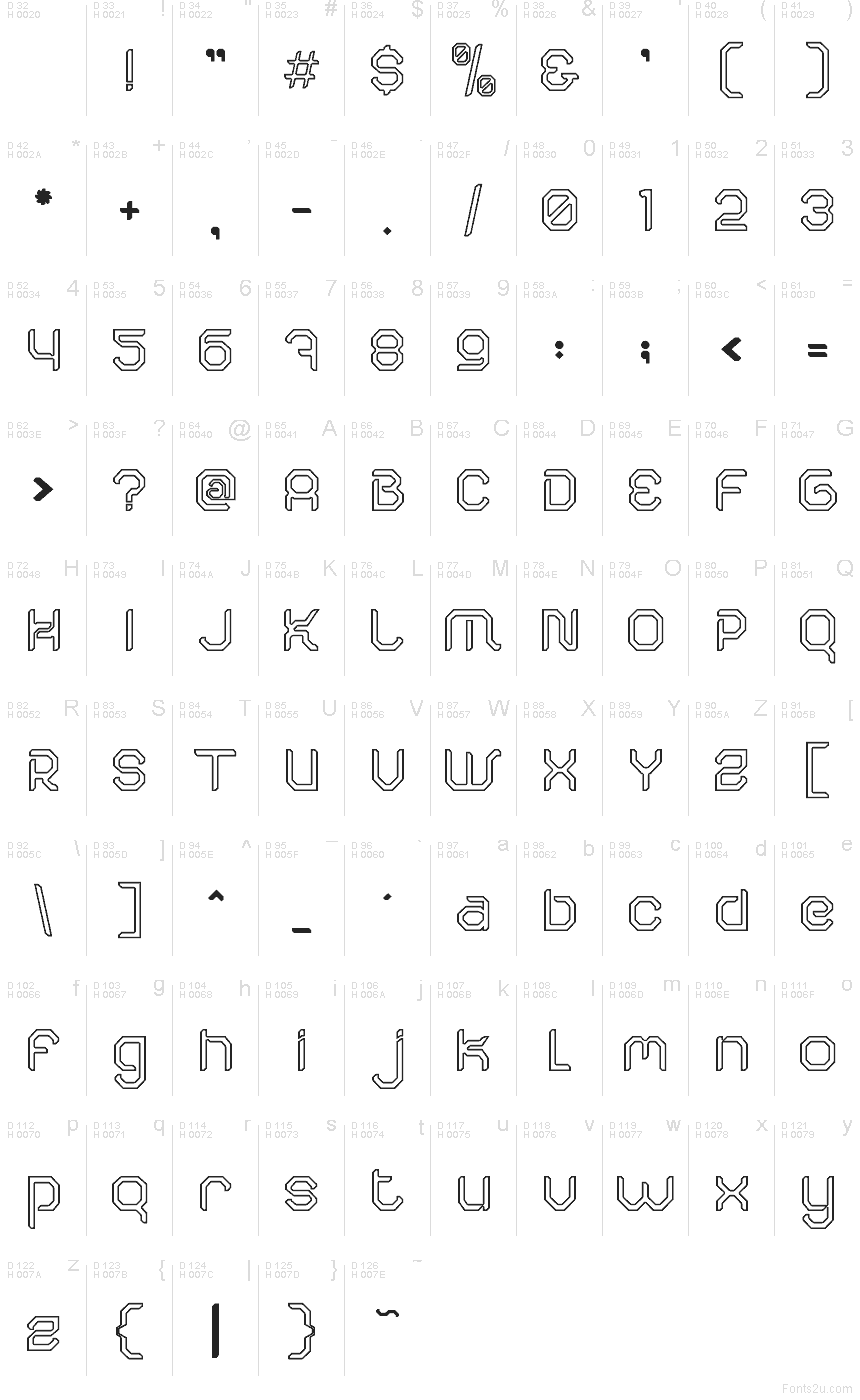
Snapshock Three
Snapshock Three od Putracetol Studio je bezplatné futuristické písmo typu display, definované ostrými skosenými rohmi a prázdnou siluetou pripomínajúcou obvody. Opakované uhlové rezy dodávajú písmenám geometrickú napätosť, zatiaľ čo otvorený obrys mu dáva ľahšiu, technickejšiu prítomnosť než u bežných robustných techno fontov.
Táto kombinácia sa skvele hodí pre herné tituly, sci-fi plagáty, grafiku technologických udalostí, obaly albumov a branding inšpirovaný používateľským rozhraním (UI), kde linky môžu odkazovať na obrazovky, panely a drôtené modely. Písmo vynikne najmä v krátkych nadpisoch a logách, kedy chcete dosiahnuť digitálny efekt bez toho, aby ste stránku zaplnili hustými čiernymi plochami.